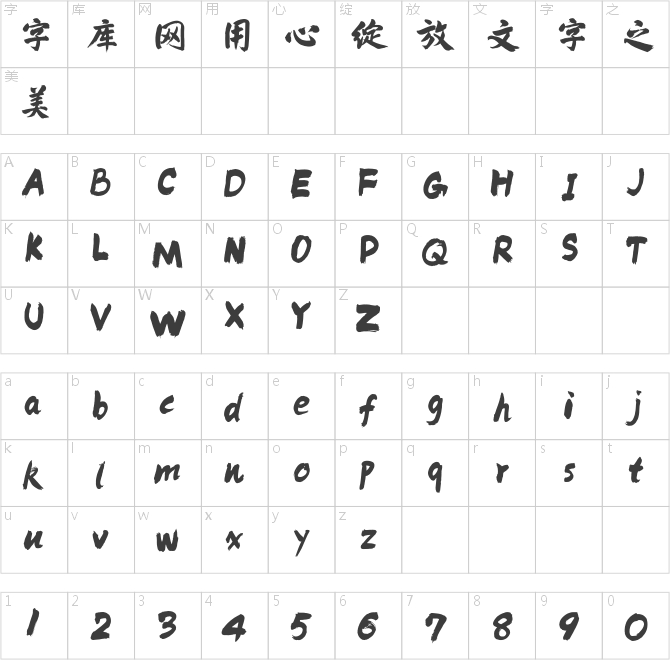
方正俠客體 簡 詳情頁
字體名稱: 方正俠客體 簡
方正俠客體 簡
方正俠客體 簡字體FZXiaKTJW字庫是一款讓人賞心悅目、百看不厭的中文字體,適合各類廣告和產(chǎn)品包裝設(shè)計應(yīng)用,字體大小16.79MB,格式為TTF字體,上傳用戶是林小瑾,作者/版權(quán)方為方正字庫